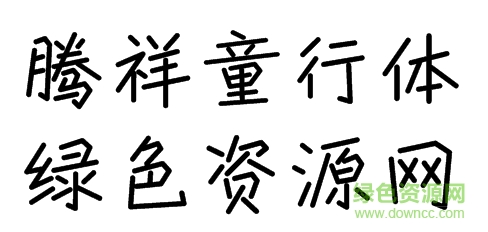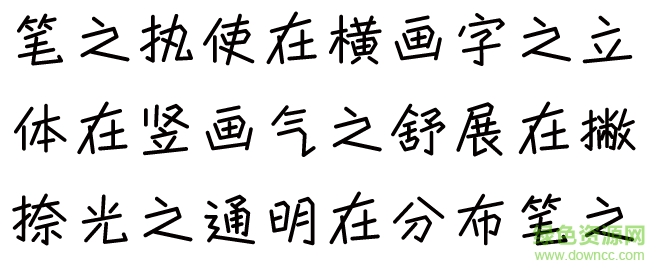
騰祥童行體是一款字跡活潑秀氣的兒童行書字體,字里行間流露著孩子的稚趣和童真,給人流暢整潔的美感,字跡穩(wěn)重而不輕浮,讓你的創(chuàng)業(yè)大放光彩,綠色資源網(wǎng)今日推薦!
此款字為手繪美術(shù)字體。風格鮮明、特點突出。筆畫舒展流暢,頓挫有秩;筆畫間相互呼應(yīng)且張弛有度;字面大小均勻,筆畫規(guī)范。整款字透顯出行書行筆特點,然而又打破傳統(tǒng)書法概念運用新的手寫方法形成一款生機盎然、清新活潑的字體,本款字在不影響閱讀的前提下盡顯其特性。本作品可適用于印刷排版兒童讀物、包裝設(shè)計、廣告設(shè)計、網(wǎng)頁設(shè)計、屏幕顯示等媒體。
騰祥童行體十分耐看,造型端正、整體協(xié)調(diào),有著極佳的視覺呈現(xiàn)和整體效果,可以廣泛應(yīng)用于廣告設(shè)計、宣傳海報、ppt、影視制作等場合。